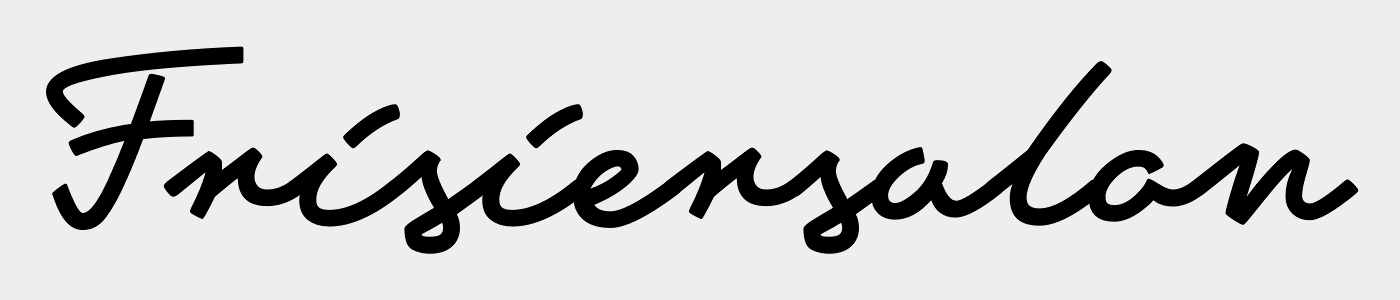
Passende Schrift im Fliesstext zu Schreibschrift als Header (Hochzeit)
Bei meinem vorherigen Eintrag wurde mirbereits sehr kompetent geholfen, sodass ich hoffe, dass Ihr mir mit Eurer Expertise bei meinem nächsten Schritt behilflich sein könnt.
Ich habe bereits (über dieses Forum) eine Schriftart ausfindig machen können, die in einer Reihe von Drucksachen für eine Hochzeit als Überschrift dienen soll. https://www.myfonts.com/fonts/mawns/tamoro-script/
Meine Bitte an Euch: Wenn diese Schrift (entweder regular oder thin) als Überschrift gewählt wird, welche weitere Schriftart bietet sich dann für den Fliesstext an? Da die Schrift Tamoro bereits etwas verschnörkelt (aber nicht zu kitschig und standardmässig "Hochzeitsgenre" ist), sollte der Fliesstext etwas unaufgeregter und dezenter daherkommen.  Die Schrift Tamoro Script sollte z.B. als Überschrift auf den Speiskarten stehen, und auf den "Save the date"-, Einladungs-, sowie Dankeskarten gedruckt werden. Der restliche Text sollte dann, zu diesem dem Stil passend, in einer leicht leserlichen Schrift verfasst werden.
Ich kann dir sehr gut folgen:nicken:.
Mit Serifen würde ich dazu kombinieren:
(ist übrigens auch die Hausschrift von typografie.info :-D)
Auch gut (aber für diese Zwecke vielleicht nicht ganz passend):
Ohne Serifen:
Im Script-Font-Stil könnte man als Fließtext eventuell die Selfie oder die Guess nehmen. Allerdings würde ich die FF Tisa oder die Brandon Grotesque vorziehen, da sie sehr elegant sind, unaufgeregt, dezent nicht von dergleichen Schriftkategorie der Script-Fonts sind und trotzdem gut zu der Tamoro passen.
Edit: Was ich auch gerade sehe ist, dass die Guess sogar einen (nur Versal)Sans Serif Schnitt hat, was natürlich sehr praktisch ist, da man so Script und Sans Serif sehr einfach kombinieren kann!
Die Schrift Tamoro Script sollte z.B. als Überschrift auf den Speiskarten stehen, und auf den "Save the date"-, Einladungs-, sowie Dankeskarten gedruckt werden. Der restliche Text sollte dann, zu diesem dem Stil passend, in einer leicht leserlichen Schrift verfasst werden.
Hilfreich wäre es vielleicht, wenn du zu formulieren versuchst, was du mit »diesem Stil« meinst. Eine schwer lesbare und unnatürlich gespreizte Schnurzugschrift – ich finde dazu keine passenden Adjektive. Ist das elegant? Ich würde es eher undeutlich nennen. Modern? Wenn Unklarheit modern ist, ja. Schwungvoll? Mir fällt dazu nicht viel ein. Ich finde sie eigentlich nur, um es möglichst neutral zu sagen: sperrig.
Wenn die Überschriften sehr groß sind und die Texte wesentlich kleiner, gibt es fast keine unpassenden Schriften wegen des großen Größengegensatzes. Eine zweite Schreibschrift, wie es Designfreak vorschlägt, kann ich mir nicht vorstellen. Daß die Beispiele so unbeholfen aussehen, liegt sicherlich auch daran, daß in den Mustern keine Buchstaben automatisch ersetzt werden. Man müßte da vieles ersetzen. In kleinen Graden dürften diese beiden aber kaum noch lesbar sein (Dresscode in 6p Schreibschrift – da kommen die Gäste im Bieranzug, weil sie den Code nicht lesen konnten); zusammen mit der schwer lesbaren Überschrift würde das wohl ein ziemlicher Linienbrei, der einen Beipackzettel mit Übersetzung erforderte.
Wenn ich einen Rat geben sollte, würde ich versuchen, dir »die Tamoro« auszureden, weil es so mühselig ist, sie zu entziffern. Sie ist im übrigen unnatürlich zusammengesetzt. Ich kenne die Alternativbuchstaben nicht, aber wenn ich das »rte« am Ende von »Speisekarte« sehe, verliere ich die Zuversicht, daß man diese Schrift überhaupt setzen kann. Das kleine »h« ist nur ein undefinierter Krakel. Wenn man dann eine gute Schrift gefunden hätte, wäre die Frage, wie die Texte dazu angeordnet sind und wie stark die Größenunterschiede sind. Das müßte man dann schon skizzieren, und zwar zuerst in irgendwelchen Typen ohne Serifen und mit Serifen, um erst einmal grob die Richtung zu ermitteln. Wie lebhaft soll die Drucksache denn aussehen? Welche Stimmung soll sie ausstrahlen, und wird das mit Schrift oder mit Farbe und Papier und Druckverfahren erreicht? Man kann schlecht erst eine extrafeine Serifenlose auswählen und dann in rosa drucken, sie wird unleserlich (so machen das Designer von Shampoo-Flaschen); man kann auch schlecht eine Fette in schwarz drucken, das wird düster. Wird die Fette aber in sehr weit gesperrten Versalien und in einem helleren Ton gedruckt, ein warmes Grau etwa, mit roten Überschriften, kann das lebhaft und harmonisch sein. Jedenfalls für kurze Texte. Welche Textschrift zur Überschrift paßt, müßte man schon in einem Beispielsatz, etwa der Einladung als wichtigster Drucksache sowie mit der textreichsten Drucksache, experimentell ermitteln, also probieren, und zwar mit den vorgesehenen Farben, zumindest annähernd. Für kurze Texte in kleinen Graden kommt es auf die Feinheiten der Schrift weniger an als auf den Schnitt. Zu einer breitlaufenden Schreibschrift kann eine schmale Serifenlose einen schönen Kontrast bilden, aber lange kleine Texte in breiten Spalten möchte man damit nicht lesen. Es kommt also auch auf die Textsorten an, die du verarbeitest, d.h. auf die Längen.
In kleinen Graden ist jede gewöhnliche Satzschrift »unaufgeregt und dezent«, frage also lieber nach der gewünschten Ausstrahlung. Serifenlose Schriften sind meistens einförmig und trostlos und werden seit 200 Jahren für modern gehalten, sie stehen an jeder Ecke herum. Gut angeordnet, können sie elegant werden und an Orte und Zeiten erinnern, als Stil-Zitate. Die Garamond ist in kleinen Graden eine stabile Schrift für Romane. Für eine Hochzeit kann es etwas spitziger sein – Caslon, Baskerville und ähnliche (vorklassizistische) sind bewährt. Serifenbetonte Schriften wirken zuerst technisch, konstruiert und kalt. Also öde wie Serifenlose, dazu aber noch an Maschinen erinnernd. Auch diese Wirkung kann man mit Farben und Anordnung wirkungsvoll unterlaufen. (Und es gibt ein paar Ausnahmen, die vor allem schmaler gezeichnet sind und deshalb etwas von der technischen Konstruktionskälte verlieren.) Und solche faden Schriften können als Kontrastmittel zu bestimmten Schreibschriften wirken. Zur Schnurzugschreibschrift sind Serifenlose und Serifenbetonte allerdings wirklich ziemlich traurig.
Daß ich »die Tamoro« für eine Kritzelsammlung halte, die ich nicht Schrift nennen würde, ist wahrscheinlich schon klar geworden, deshalb werde ich es nicht noch eigens erwähnen.
Es ging mir in erster Linie darum, eine Schrift zu finden, respektive Drucksachen für eine Hochzeit zu verfassen, die nicht dem "08/15 Hochzeitskartenkitsch" (Schnörkelschrift und Herzchen und Luftballons am Rand) zuzuordnen sind, den man überall begegnet, wenn man sich (online) nach Hochzeitskarten umschaut.
Die Hochzeitslocation ist ein altehrwürdiges Hotel (seit über 350 Jahren in Familienbesitz), in dem auch noch einige alte Schriftzüge anzutreffen sind (siehe Anhang).  Hier hätte ich einfach gerne diesen Einfluss aufgenommen und in ein modernes Format für die Drucksachen übertragen. Mir ist bewusst, dass sich diese Schnurzugschreibschrift eben nicht als Fliesstext eignet. Folglich die Überlegung, dass man diesen Einfluss wenigstens in den Überschriften anbringen könnte und dann eine etwas ruhigere Schrift für den restlichen Fliesstext auswählt.
Wir können ja hier gemeinsam mal noch ein paar weitere und bessere Schnurzug-Schreibschriften* passend zu Deiner Vorlage zusammentragen. Und wenn wir dann etwas Brauchbares haben, schauen wir nochmal, was man dazu kombinieren kann. :-D
@RobertMichael hatte neulich schon in einem anderen Thread ein paar – wie ich finde – reizvolle Exemplare vorgestellt. Find den aber momentan nicht …